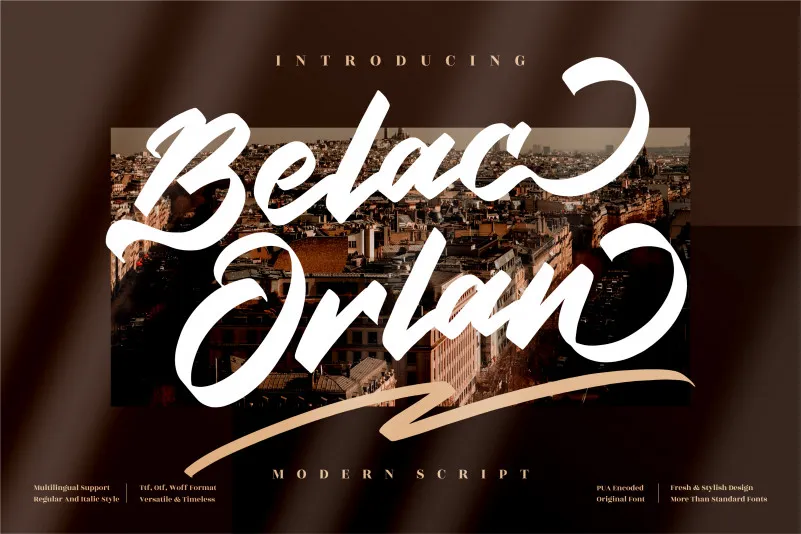
A Belac Orlan Font é uma elegante fonte à mão livre que pode ser usada em uma variedade de projetos criativos para trazer um toque sofisticado e único aos seus designs. Feita de forma manual, esta fonte foi projetada para atender a uma ampla gama de necessidades de design, incluindo logotipos, projetos de marca, designs de casa, embalagens de produtos, taças de café, citações, cartazes, sacolas de compras, camisetas, capas de livros, cartões de nome, convites e aniversários, etiquetas, fotografias e até mesmo logotipos. A Belac Orlan é a escolha perfeita para aqueles que desejam dar um toque autêntico a seus projetos, seja em uma marca personalizada ou em itens de decoração que você usa todos os dias. Além disso, o designer perspectype investiu muito tempo e cuidado na criação desta fonte à mão livre para garantir que ela tenha um estilo único e versátil. Seja para um projeto de design digital ou uma criação impressa, a Belac Orlan é ideal para atender às suas necessidades. Este é um excelente exemplo da qualidade do trabalho do designer perspectype, destacando-se como uma fonte à mão livre perfeita para quem busca um toque autêntico e sofisticado em seus designs.